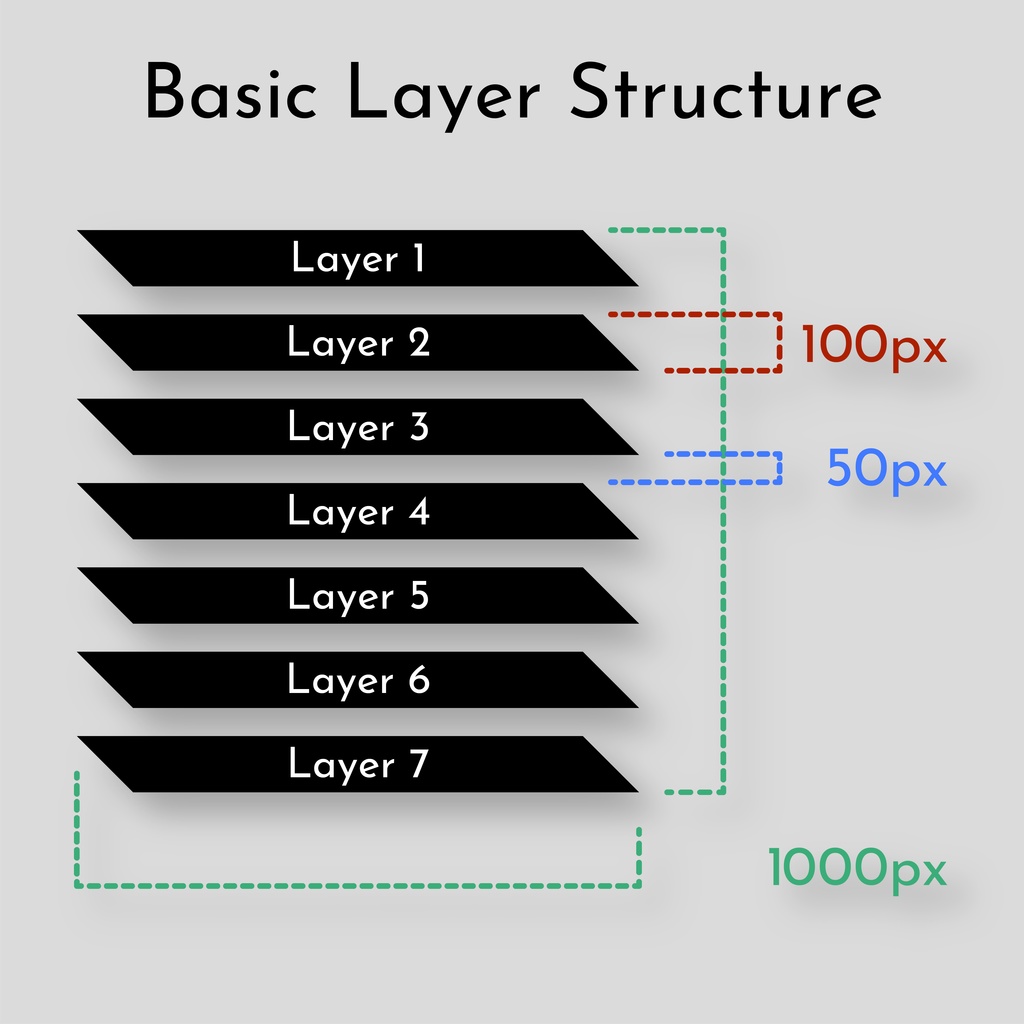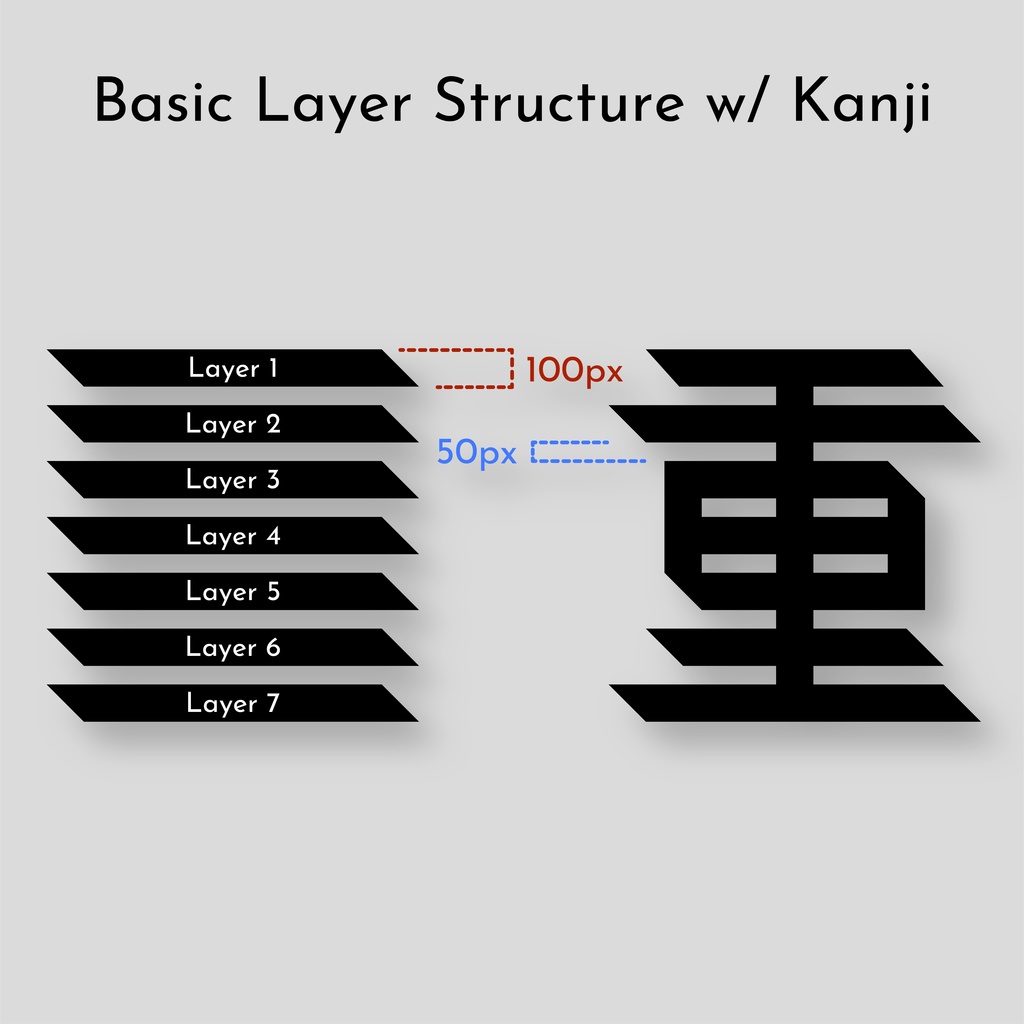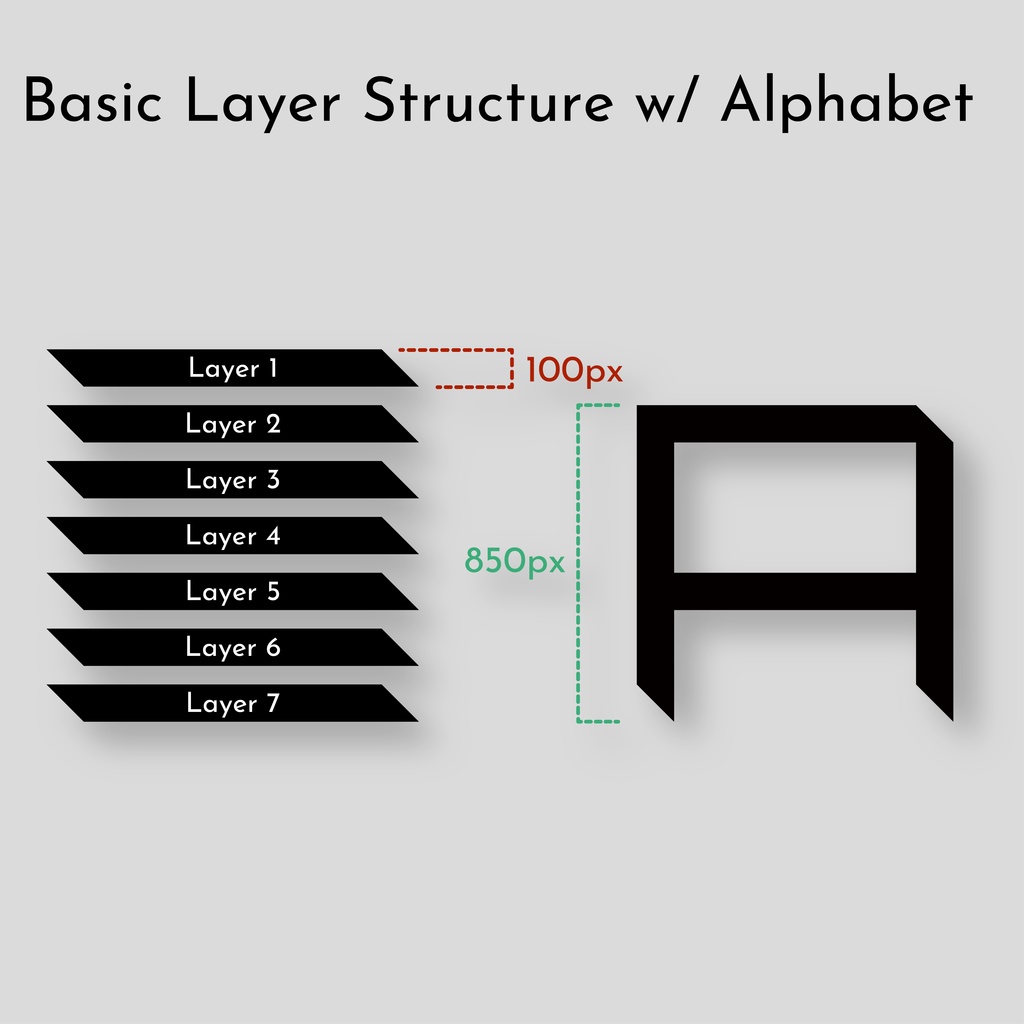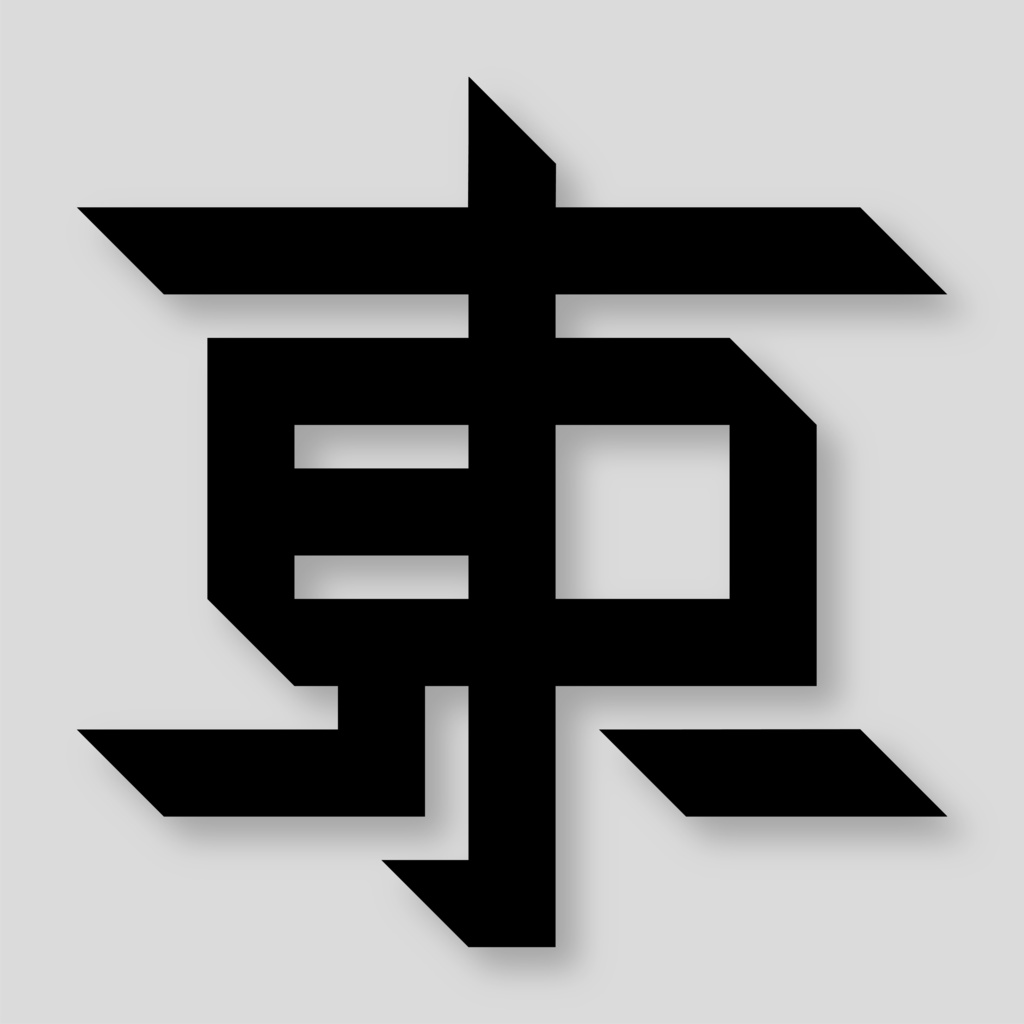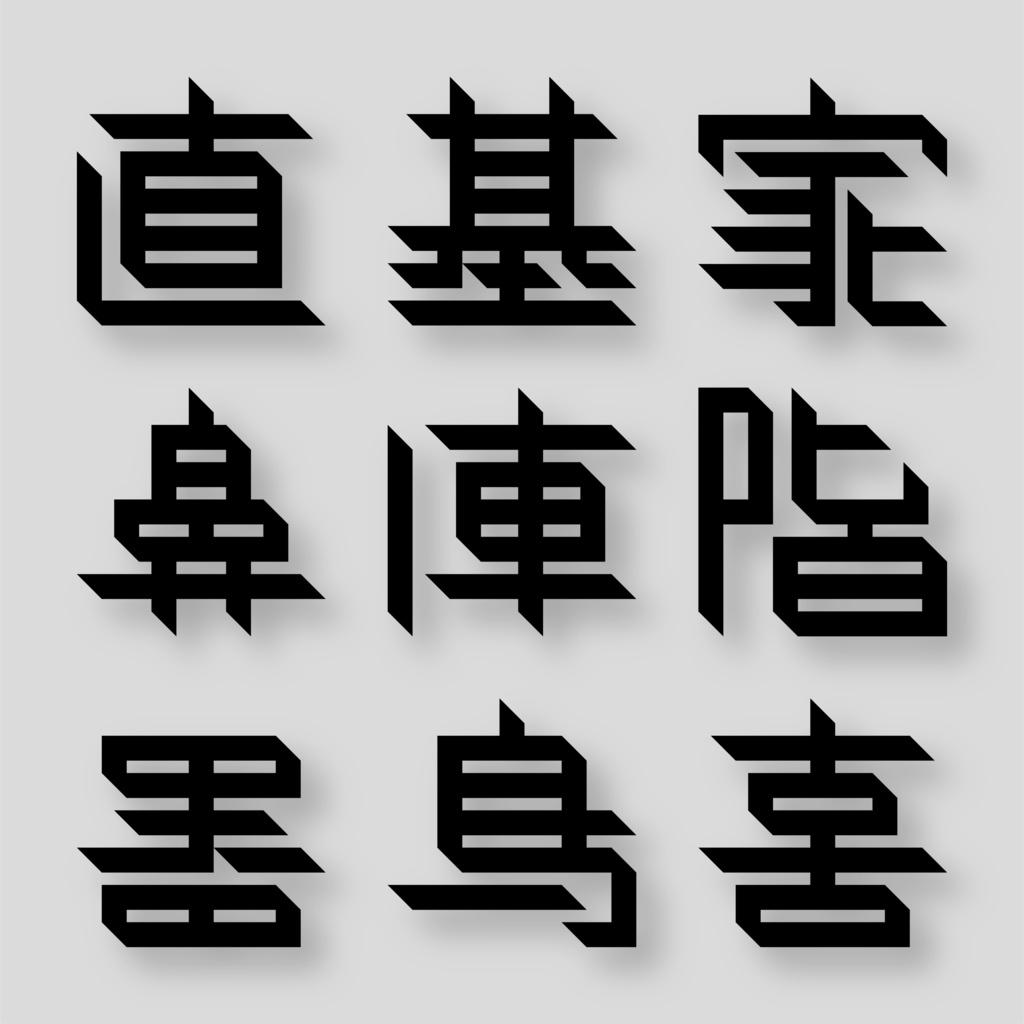
階層フォント / Layer Font
大学の卒業制作で作ったフォントです。 レイヤー構造の見られる「駅構内立体図」をただの地図ではなく、漢字のようだと感じたことに端を発した制作となります。 また、統一されたレイヤー構造を用いて各グリフを作成したため、隣接する文字同士で画を接続することが可能となっています。 お気に召す方がいらっしゃれば幸いです。
特徴
☆ 階層性 「駅構内立体図」に触発され、その階層性に着目したフォントなので、階層性を用いたタイポグラフィやロゴ制作に向いています。 ☆ 省略 画数の多い漢字は画の省略を行うことで、その字の面影を残しつつ程よい余白感を実現しました。 省略については「東亜重工(https://toahi.net/)」、「真四角書体(https://moji-design.stores.jp/?category_id=61d7ba0fe3bbd1665b6f7daf)」、『東亜新字(著・前田黙鳳)』などを参考にしたり、独自のアレンジを施したものもあります。 ☆ 接続性 統一されたレイヤー構造を元に各グリフを作成したので、隣接する文字の画同士を接続・屈折が容易です。 そのため、熟語を1つの文字に見えることや、文字であるのに図や迷路のように見せることができます。 画像5枚目は「東」と「京」を組み合わせた作例となります。 ☆ 字形 漢字には以下3種類の字形があります。 画像6枚目はその字形の例です。 •楷書体とおおよそ同じ字形(上) •独自の省略を行った字形(中) •旧字・異体字・俗字、調査した既存書体を参考にした字形(下)